Строчная «г» в рукописном шрифте: как удержать её форму в общем стиле
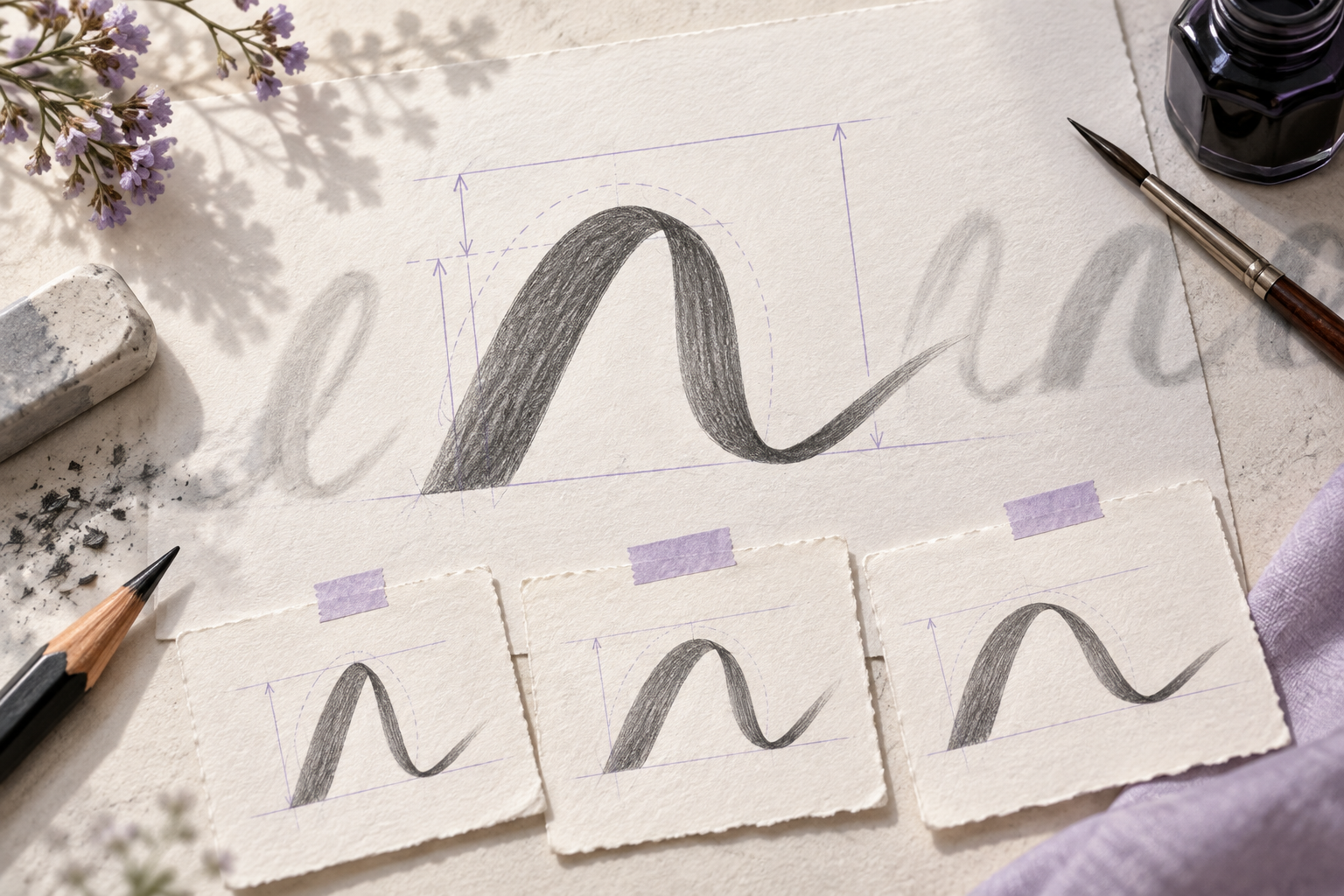
Строчная «г» в рукописном шрифте должна оставаться узнаваемой в короткой изолированной форме и при этом выглядеть частью того же алфавита, что «а», «н» и «у». Для этого полезно сначала определить её собственный силуэт, затем согласовать высоту, ширину, наклон и характер переходов с уже нарисованными буквами. Ниже — практический порядок, который помогает избежать случайной формы и проверять её не только отдельно, но и в словах.
Почему строчная «г» требует отдельного решения
У многих букв есть заметная внутренняя область или несколько штрихов, по которым глаз быстро узнаёт знак. У строчной «г» рисунок компактнее: небольшое изменение плеча, верхнего хода или длины штриха может заметно поменять впечатление. Если сделать знак слишком прямым, он будет казаться чужим среди округлых букв; если подчеркнуть изгиб чрезмерно, он станет декоративным акцентом и нарушит спокойный ритм строки.
Сложность не в поиске единственной правильной формы. Рукописная гарнитура может опираться на конкретный почерк, на геометрически упрощённую конструкцию или на более каллиграфический жест. Задача автора — выбрать логику, объяснить её через соседние знаки и применять последовательно. Перед тем как исправлять «г», полезно спросить: что именно не работает — узнаваемость, пропорция, направление движения или согласованность с остальными буквами?
Начните с наблюдения, а не с обводки
Соберите несколько естественных образцов своей строчной «г»: напишите её отдельно, затем в коротких словах и фразах. Не выбирайте самый красивый отдельный экземпляр автоматически. Ищите повторяющиеся решения: где рука начинает движение, как меняет направление, насколько широко раскрывает верхнюю часть, чем заканчивает штрих. Один случайный росчерк может быть удачным в надписи, но неудобным как основа знака, который должен много раз повторяться в наборе.
Для сравнения подойдут слова, где «г» стоит в разных позициях: «гора», «книга», «дорога», «берег», «глина». Они показывают не только рисунок, но и то, как буква входит в соседство, сколько места занимает и не сбивает ли темп. Пишите медленно и в обычном темпе: слишком аккуратная демонстрация иногда скрывает реальный жест, а торопливая запись — случайно добавляет лишние петли и дрожание.
Сначала зафиксируйте опорные параметры
До чистовой отрисовки отметьте на листе четыре ориентира: базовую линию, верх строчных, ширину корпуса и общий наклон. Для «г» особенно важна связь высоты с шириной: короткий знак не должен выглядеть ни сжатым комком, ни слишком вытянутой деталью. Сопоставляйте его не со всеми буквами сразу, а с парой характерных соседей — например, с «н» для высоты и вертикальных штрихов и с «а» для масштаба округлых элементов.
Затем выберите устройство верхнего хода. Он может быть почти прямым, мягко округлённым или заметно жестовым — это не набор украшений, а часть конструкции. Решите, насколько верх раскрыт, где находится вершина и как она переходит в основной штрих. Схематично нарисуйте несколько вариантов одним и тем же инструментом. Меняйте по одному параметру: сначала раскрытие, потом ширину, затем наклон. Если менять всё сразу, будет трудно понять причину удачного или неудачного результата.
Согласуйте штрих с характером всего алфавита
Рассмотрите «г» рядом с буквами, которые показывают правила вашей гарнитуры. Если в алфавите преобладают ровные вертикали и сдержанные дуги, резкая петля в «г» будет выглядеть отдельным приёмом. Если почерк свободный и округлый, слишком механический угол нарушит пластику. Здесь важно не копировать каждую букву буквально, а перенести общий принцип: одинаковую степень округления, похожую скорость поворота и сопоставимую контрастность штриха.
Сравнивайте не только толщину, но и то, как она возникает. В одних образцах нажим усиливается на нисходящем движении, в других линия почти равномерна. У «г» короткая конструкция может выглядеть тяжелее соседей даже при той же толщине пера — просто потому, что штрихов меньше и они собраны ближе. Сначала исправьте силуэт и расстояния между ходами; утоньшение не должно маскировать проблему формы.
Проверьте букву отдельно, в слове и в серии
Изолированный знак удобен для анализа контуров, но не показывает ритм. Составьте небольшую пробу из нескольких слов с повторением «г» и поставьте их рядом с нейтральными контрольными словами без этой буквы. Посмотрите, не появляется ли в каждой строке одна и та же тёмная точка, чрезмерный просвет или заметный скачок наклона. Если проблема видна только в сочетании, возможно, менять саму конструкцию не нужно: достаточно скорректировать боковой интервал или подход к соседнему штриху.
Проверяйте один и тот же набор сначала в рабочем размере, затем уменьшенным. Уменьшение быстро показывает детали, которые превращаются в шум: узкое раскрытие, слишком близкие штрихи, хрупкий тонкий участок. Увеличение, напротив, помогает увидеть случайные перегибы и лишние остановки линии. Это качественная проверка, а не универсальный числовой норматив: нужный размер зависит от будущего применения шрифта и способа его вывода.
Для выразительной строчной «г» достаточно ясного силуэта и нескольких согласованных параметров: высоты, ширины, раскрытия, направления хода и характера перехода. Сначала наблюдайте повторяющийся жест, затем сравнивайте варианты в словах и фиксируйте правило выбранной формы. Когда набор букв уже готов, шаблон Fontgenerator помогает перейти от ручных проб к аккуратной оцифровке и собрать собственный шрифт.